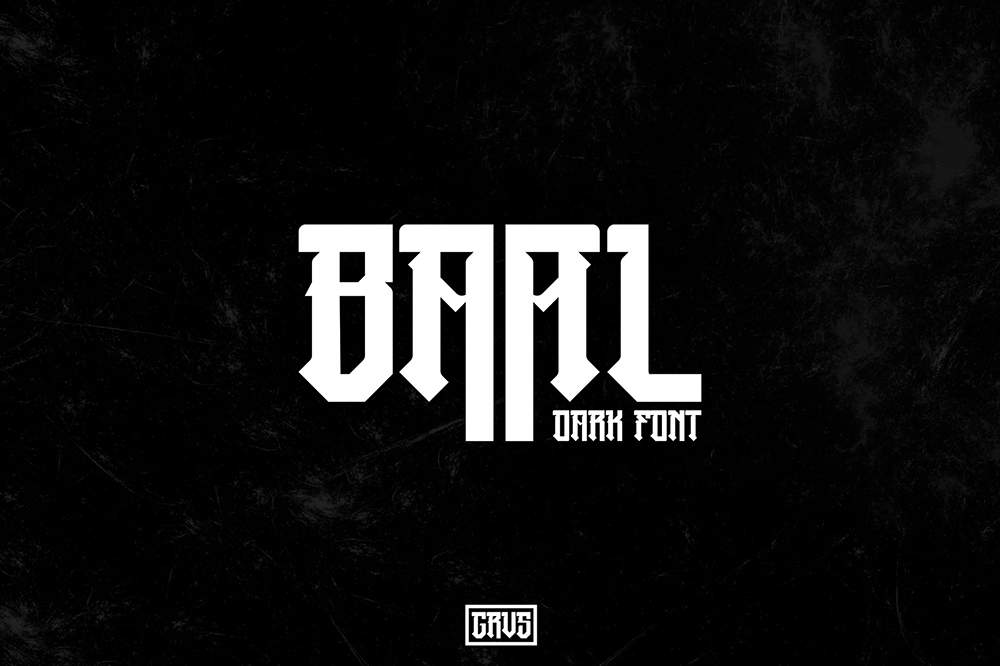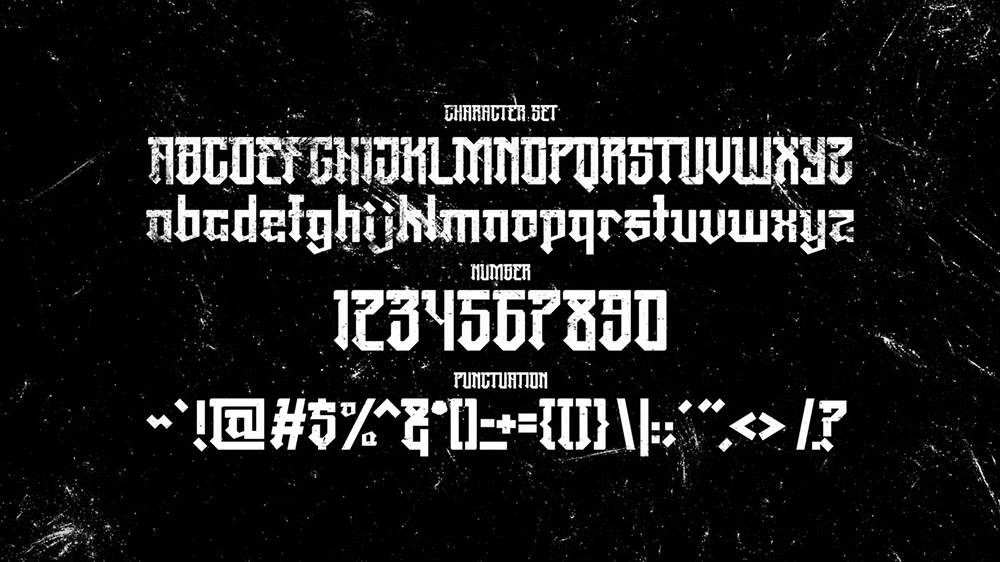
دانلود فونت انگلیسی BA AL Font
فونت پرمیوم و انگلیسی BA AL Font برای لوگوی تیم یا لوگوی انجمن با تم تیره مناسب است. BA AL دارای سه نسخه میباشد که برای لوگو، استیکر، تیشرت، کارت دعوت، بروشور و غیره عالی است.
مزایای استفاده از فونت لاتین BA AL چیست؟